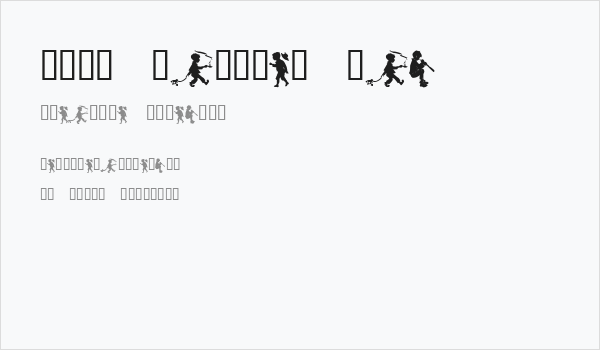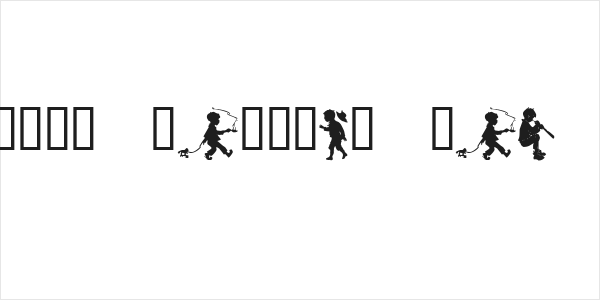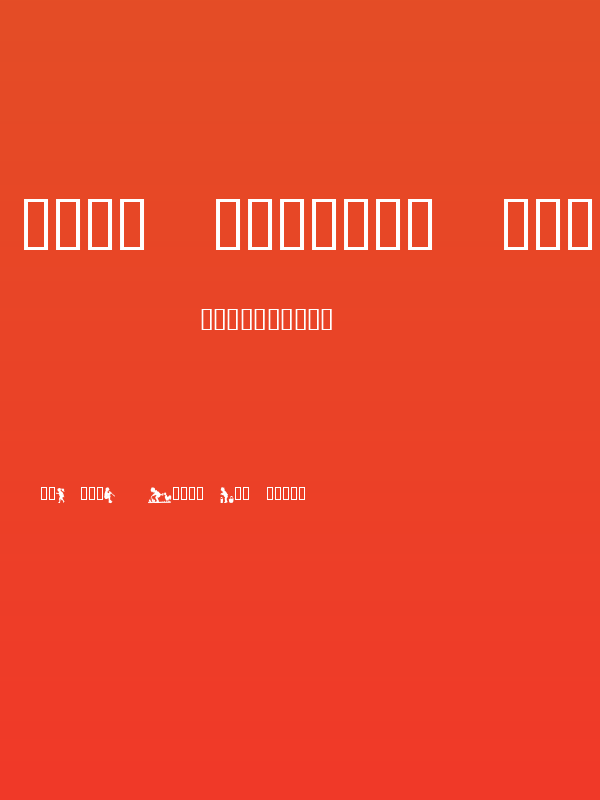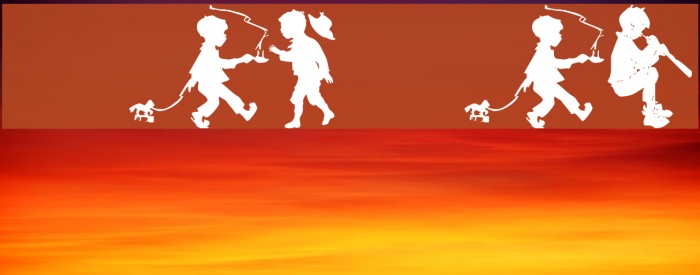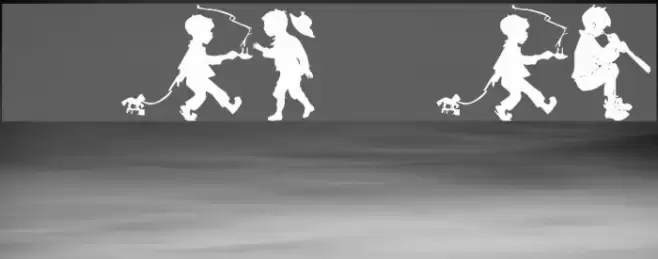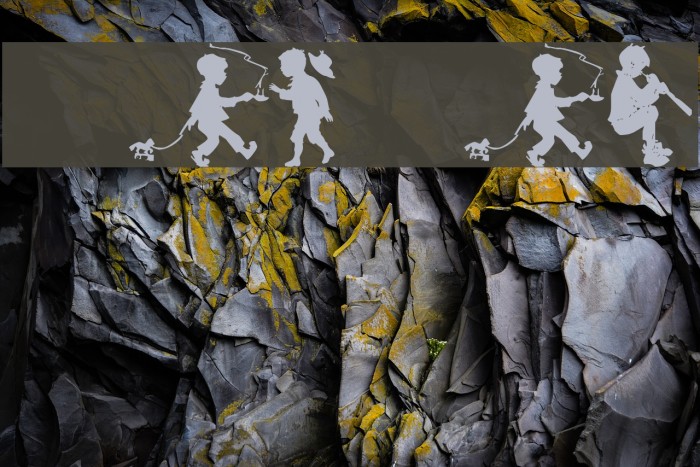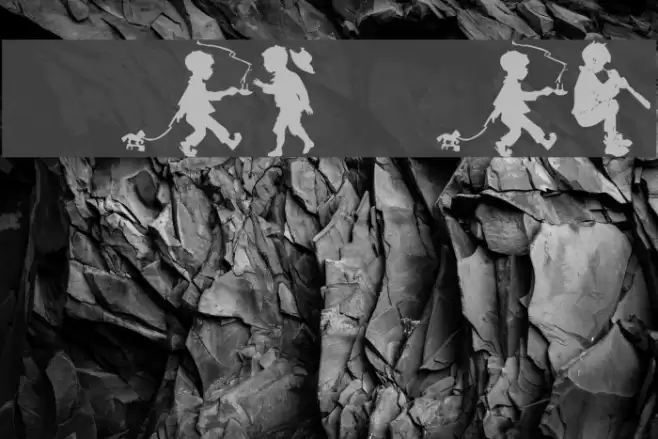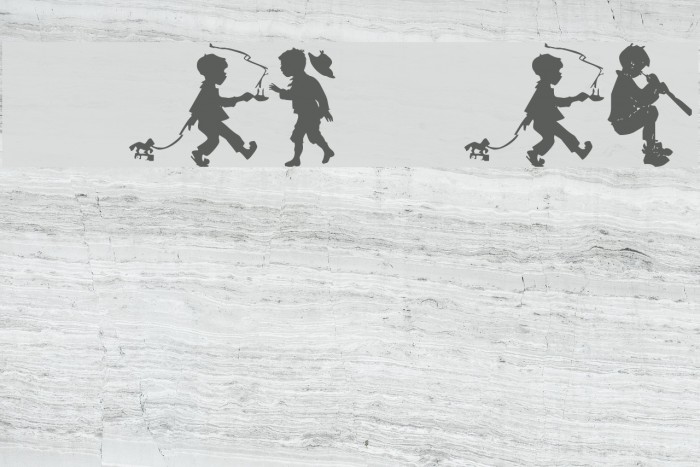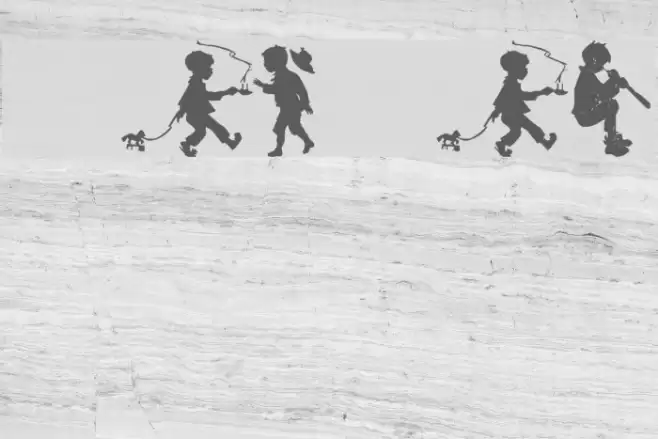
Boys Sampler Pack Font
✎ Dingbats
| حالة الاستخدام | Logos, Posters, Creative projects |
| مشاريع مقترحة | Ideal for children's book covers, playful invitations, educational materials, and creative posters. |